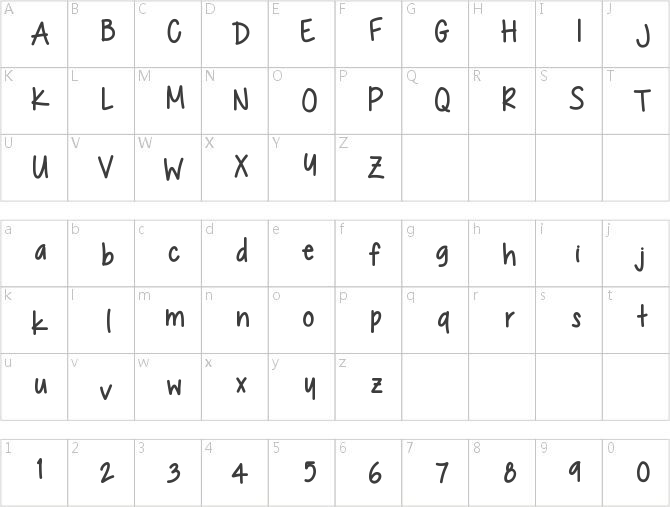
字體名稱: Chocola
Chocolate Covered Raindrops Bol
Chocolate Covered Raindrops Bol介紹
Chocolate Covered Raindrops Bol字體字庫是一款讓人賞心悅目、百看不厭的英文字體,適合各類廣告和產品包裝設計應用,字體大小0.04MB,格式為ttf字體,上傳用戶是Apple,作者/版權方為未知